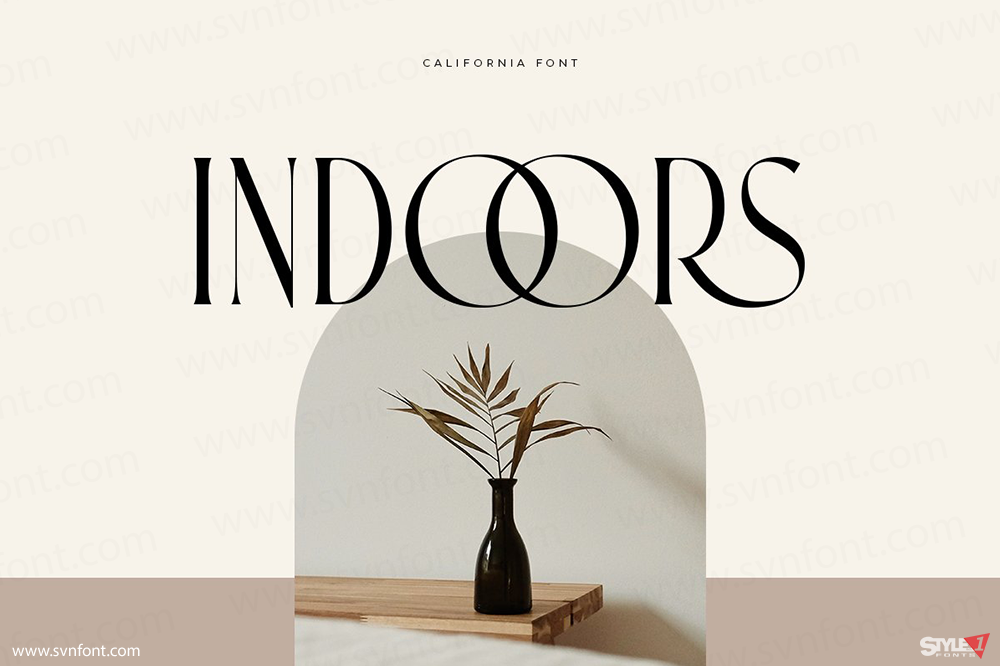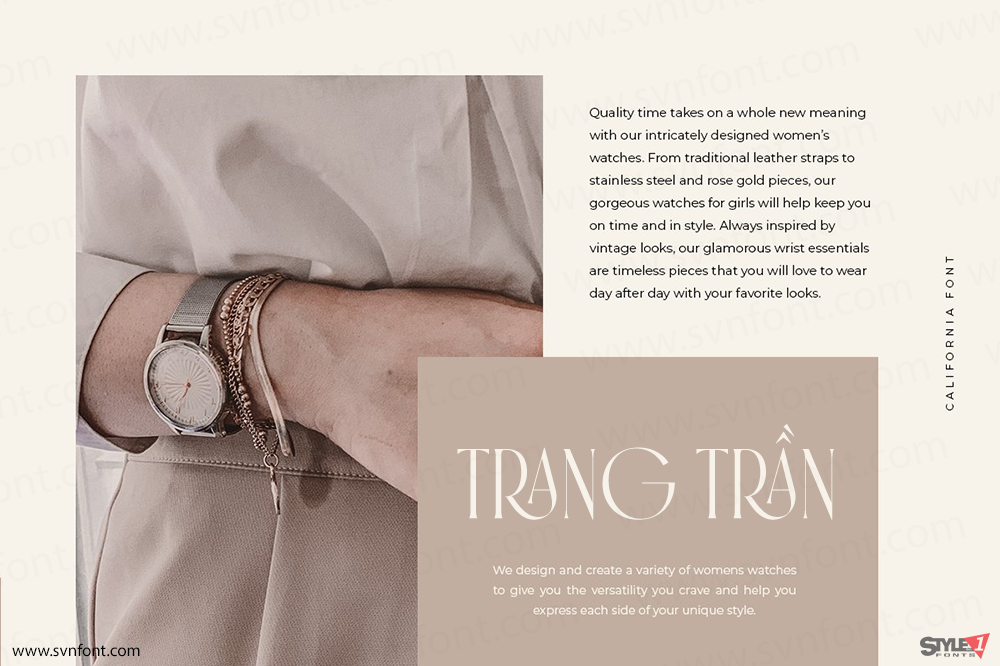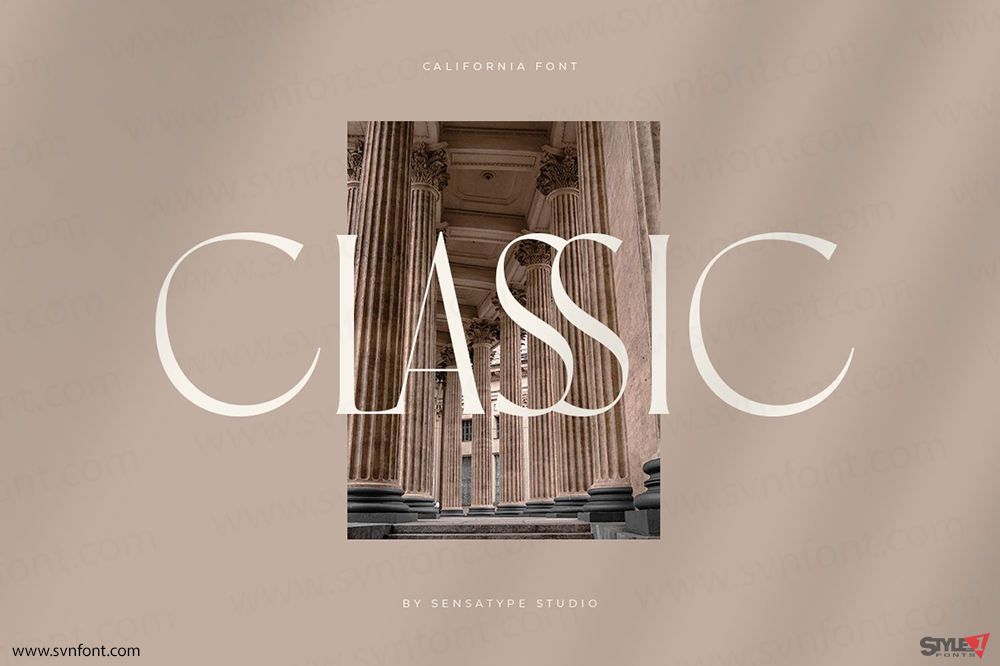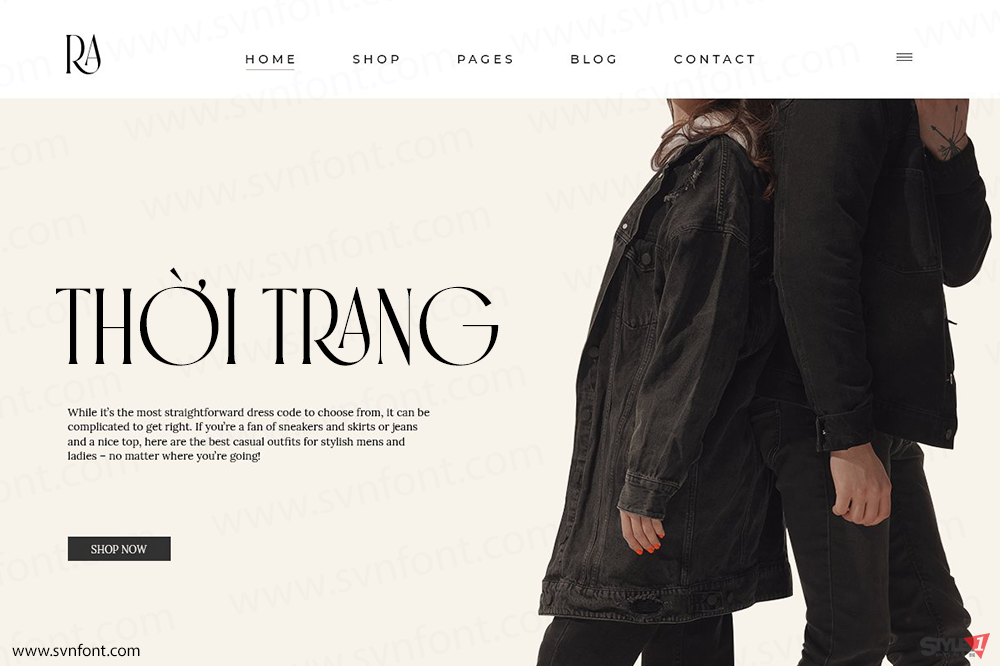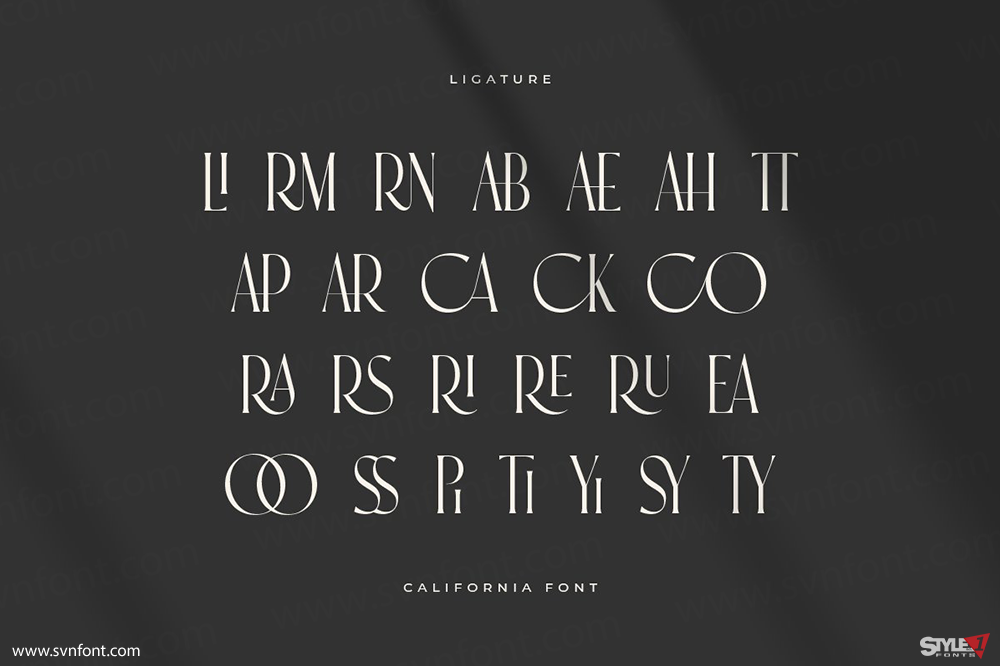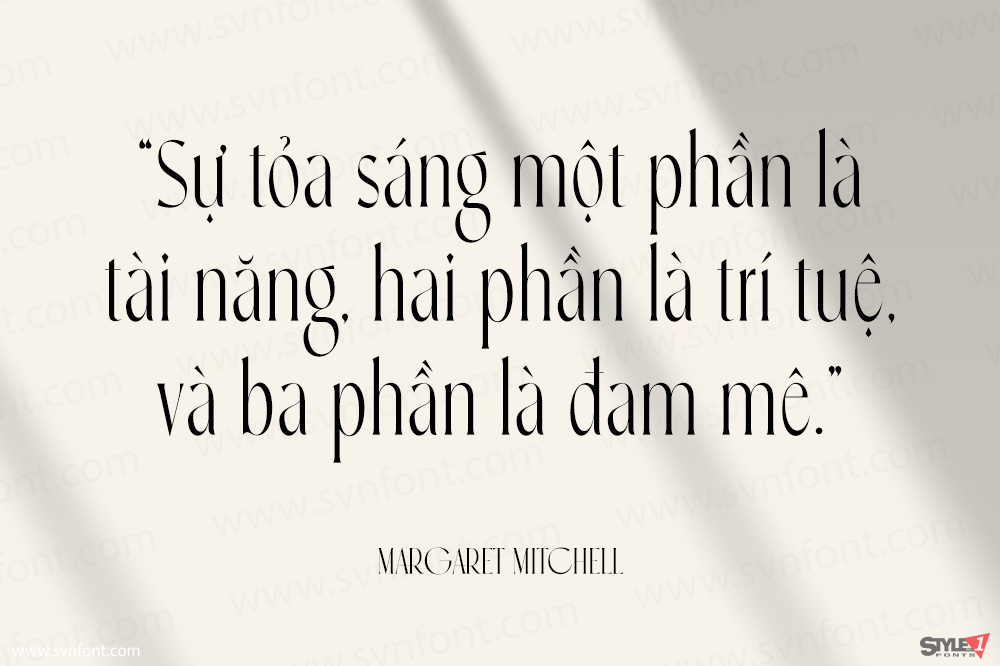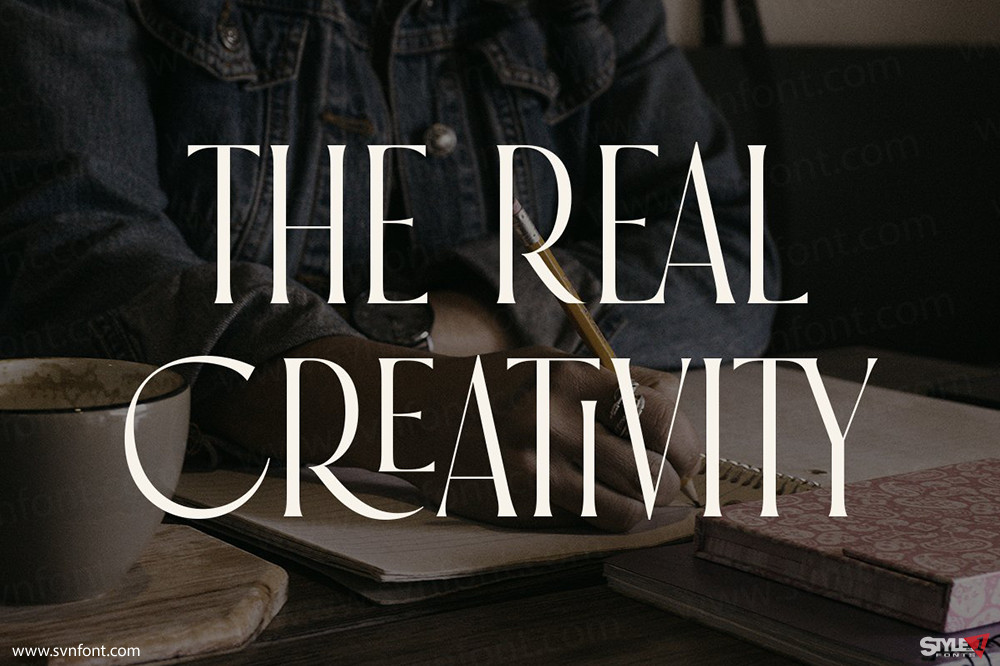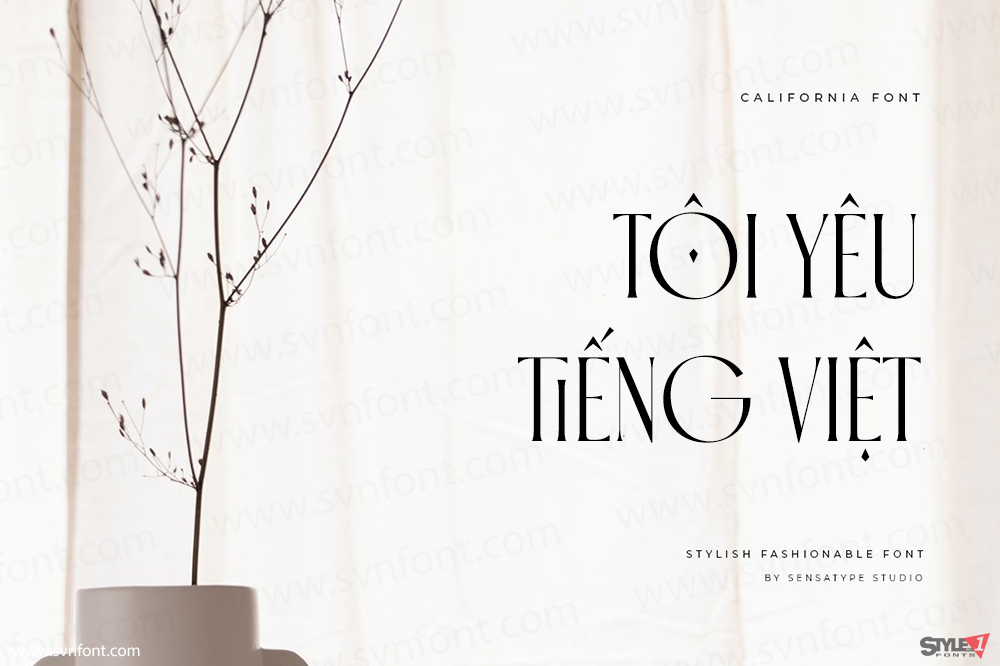
California, một font Serif Display mà chúng tôi tạo ra đặc biệt cho nhu cầu xây dựng thương hiệu đẳng cấp, với các nét nối (ligature) bổ sung theo hình dạng độc đáo và cổ điển, giúp tăng thêm giá trị cho thương hiệu của bạn. Thật tuyệt vời để hỗ trợ các nhà thiết kế hoặc chủ sản phẩm cần giải pháp để làm cho thiết kế của họ trông sành điệu và thời trang hơn. Và đặc biệt đối với font California, chúng tôi đã chuẩn bị nhiều nét nối và các ký tự thay thế (alternate characters) để giúp bạn tạo ra vô số biến thể cho nhu cầu sáng tạo của mình.
Nhà thiết kế: Zamroni Hamzah
Nhà phát hành: Sensatype